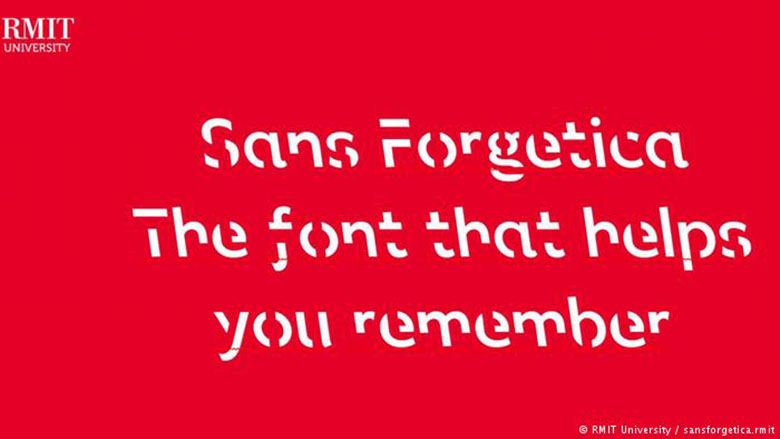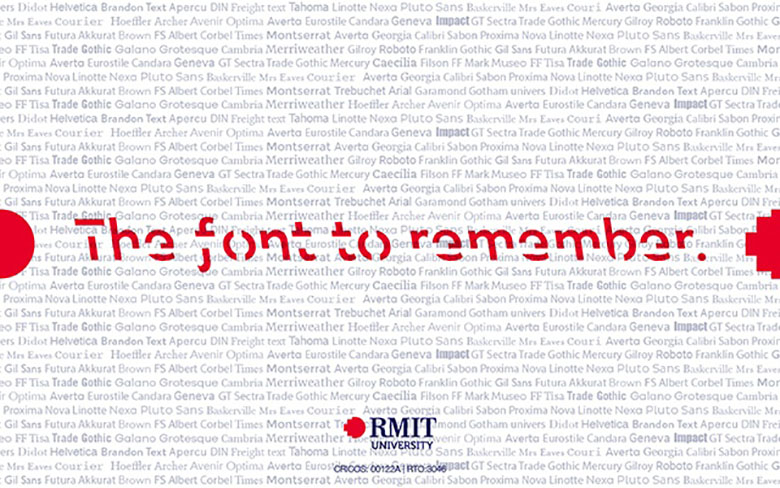
فونت عجیبی که به شما کمک میکند مؤثرتر و به میزان بیشتر خواندههایتان را به یاد بیاورید
آموختن دروس مختلف و موفقیت در امتحانات، یادگیری زبانها و کلمات جدید و یادآوری فهرست کارها برای هر فردی سخت است.
این وضعیت برای دانشآموزان و دانشجویان در روزهای امتحان سختتر هم میشود، چون ذهنشان باید چندین ساعت به طور متوالی مشغول حفظ کردن و به خاطر سپاری انواع متنها و دروس خوانده شده باشد.
حالا، تیمی از محققان انستیتوی تکنولوژی سلطنتی ملبورن فونت جدیدی نام «Sans Forgetica» طراحی کردهاند که «با استفاده از قواعد روانشناختی» به دانشآموزان و دانشجویان در به یاد آوردن مطالبی که خواندند؛ کمک میکند.
طراحی غیرمعمول این فونت باعث میشود خواندن آن برای هر فردی راحت نباشد و ذهن را درگیر یک چالش کند. ذهن برای خواندن این متن نیاز به پردازشهای شناختی عمیقتری دارد و همین موضوع باعث میشود بهتر به خاطر سپرده شود.
هرگاه ذهن نتواند یک متن را به حالت عادی و ساده بخواند؛ تلاش و پردازش بیشتری برای فهم آن انجام داده و عمیقتر به حافظه میسپارد.
فریب ذهن برای تقویت حافظه
در طراحی فونت «Sans Forgetica» از شکل و قالب فونت «Sans Serif» استفاده شده و به این دلیل بسیار به آن شبیه است ولی دو ویژگی نامتعارف در طراحی آن گنجانده شده است.
تمام حروف اندکی به سمت چپ تمایل دارند که در تایپوگرافی امری غریب و به ندرت دیده شده است.
به علاوه، حروف فونت «Sans Forgetica» پر از حفره هستند. این حفرهها باعث فریب خوردن ذهن میشوند تا بیشتر درگیر شناخت آنها شده و پایدارتر در ذهن جا بگیرند.
در آزمایشی که برای تعیین کارایی دقیق این فونت روی ۴۰۰ دانشآموز شده است و آنها متنهایی را با فونتهای مختلف مشاهده کردند؛ دانشآموزانی که متنشان با فونت «Sans Forgetica» بوده؛ ۷ درصد بیشتر از دیگر دانشآموزان در به خاطر سپاری متن موفق ظاهر شدند.
طراحان این فونت امیدوار هستند در آینده مربیان، دانشآموزان و روانشناسان بالینی از این فونت برای تقویت حافظه استفاده کرده و تاثیرات واقعی و عملی آن را مشاهده کنند.